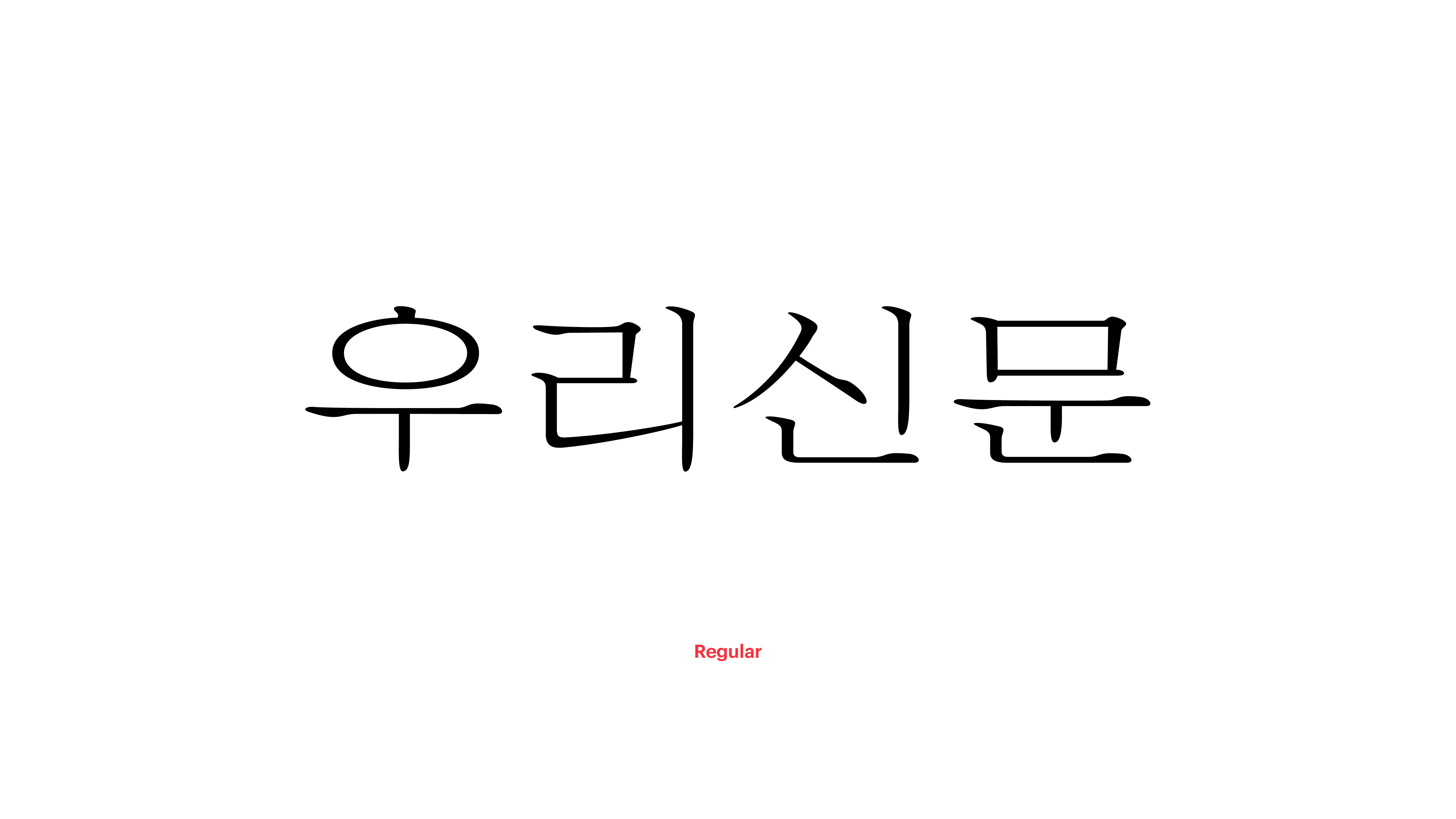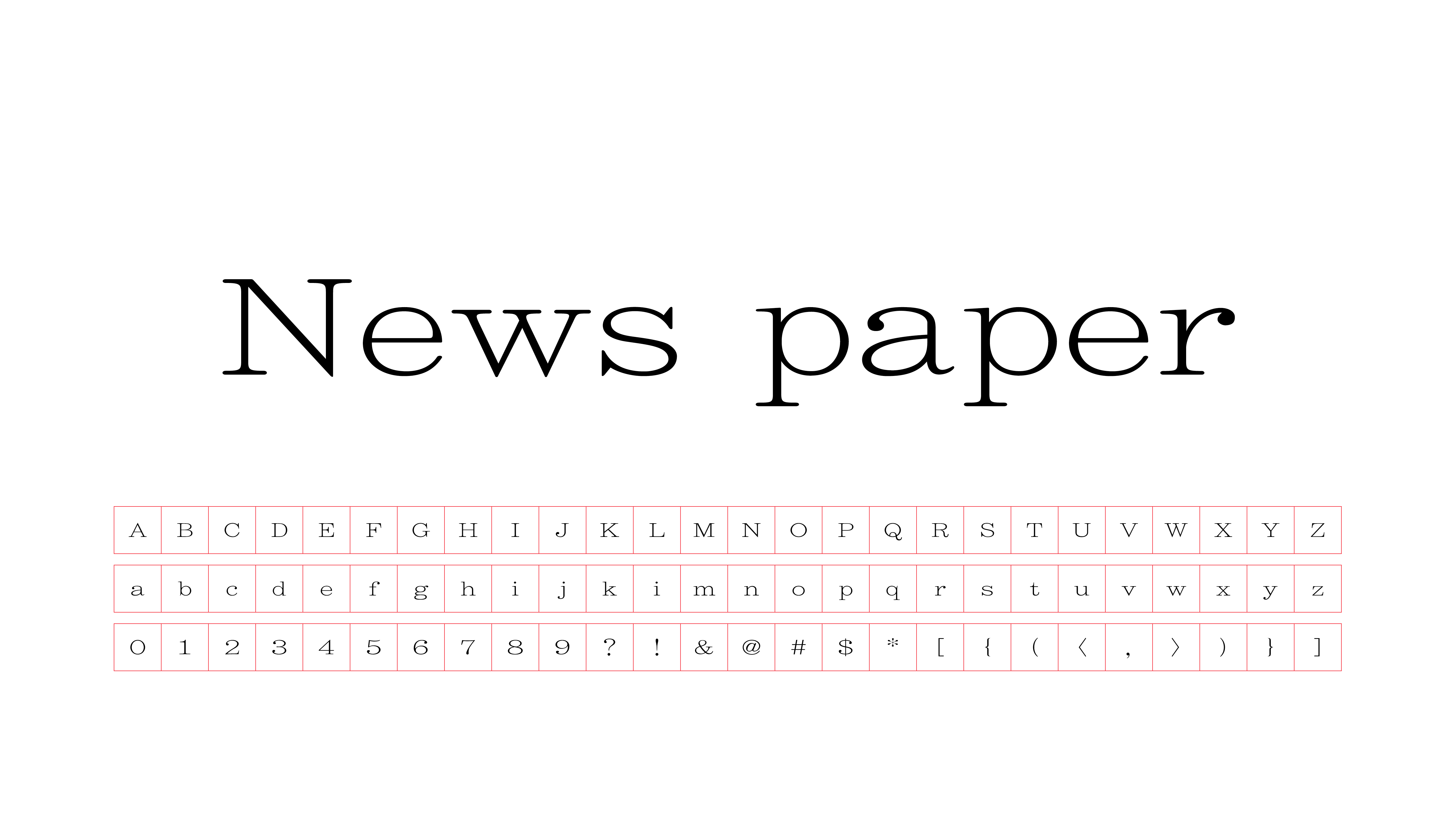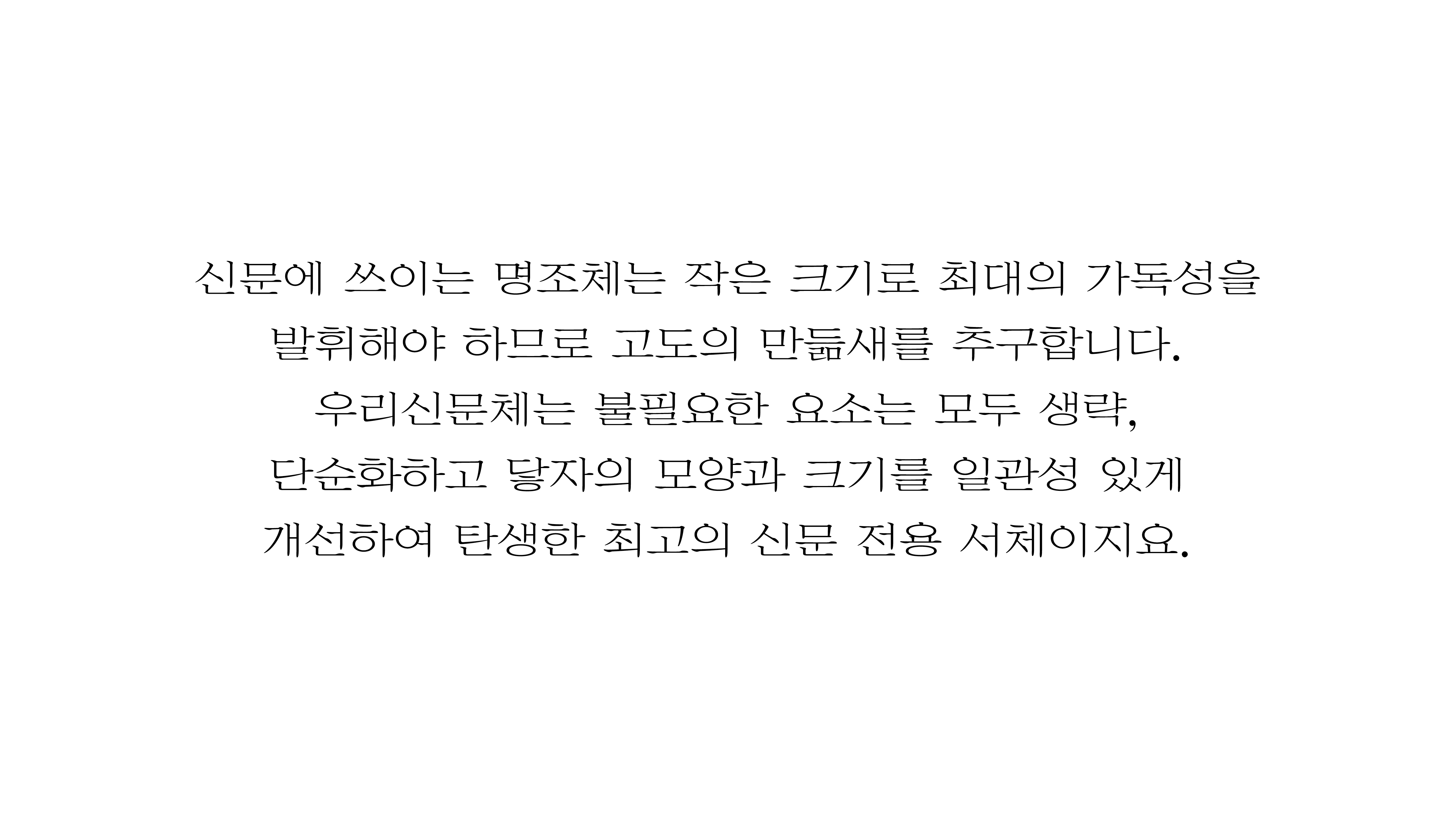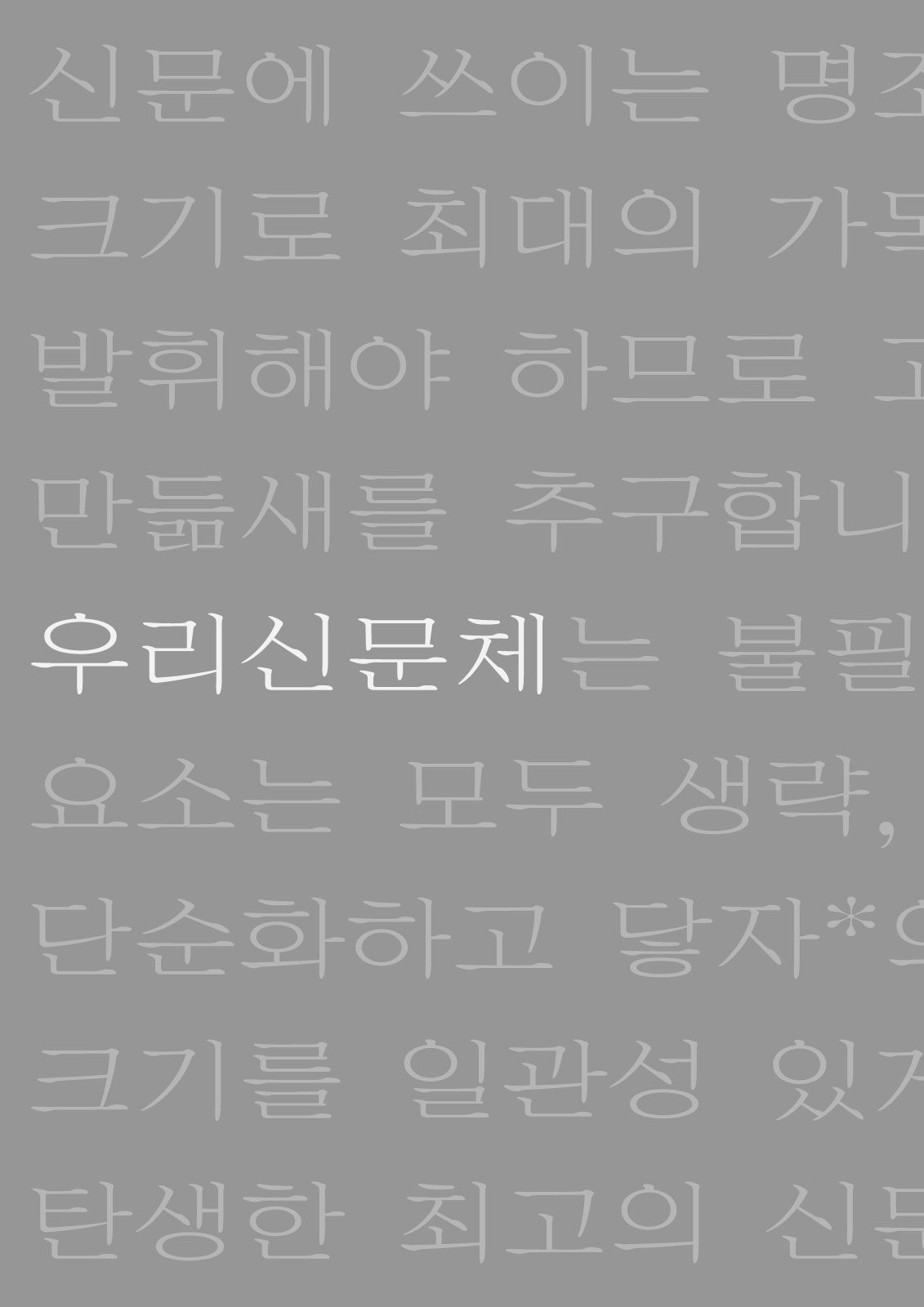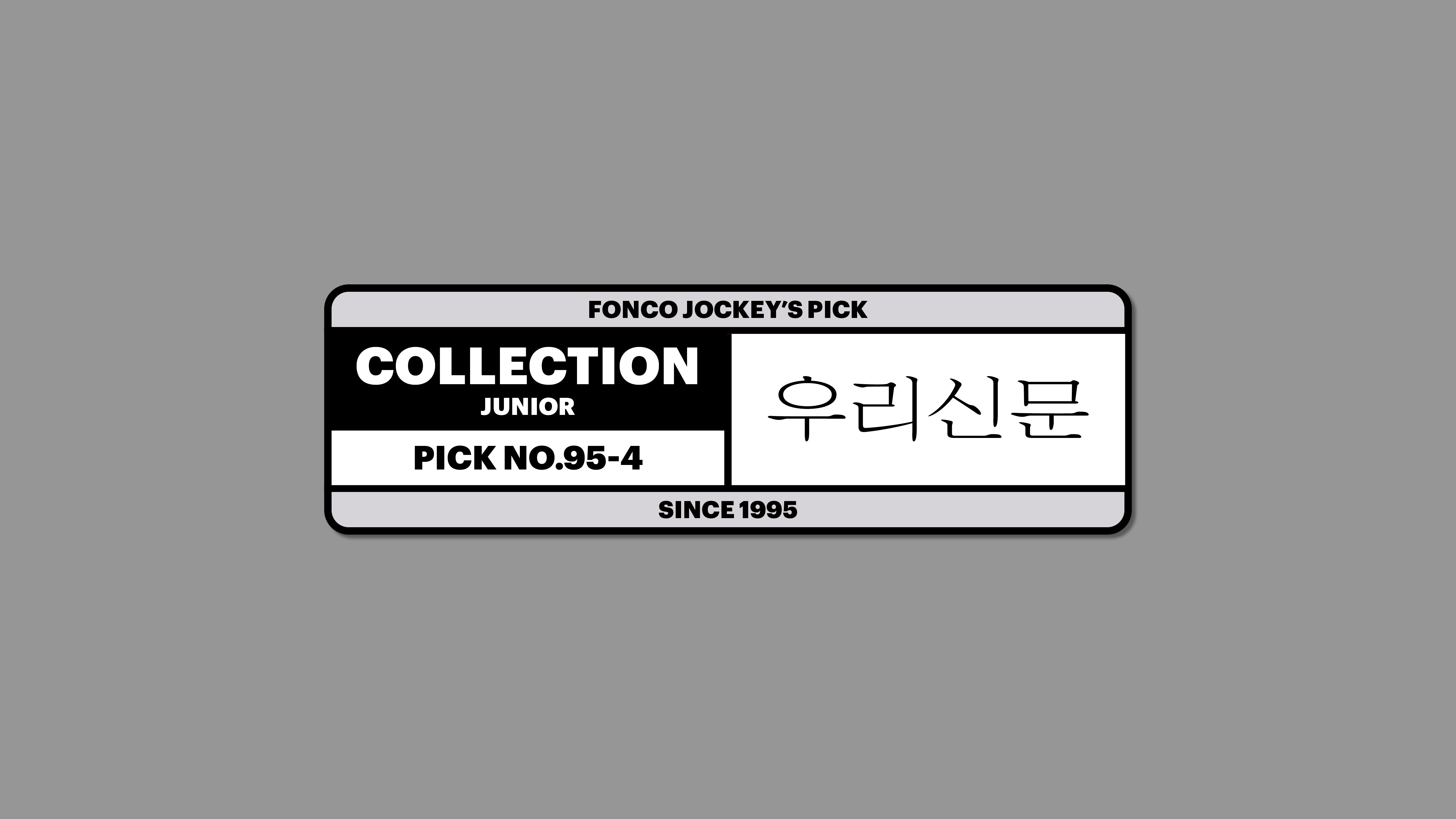
우리신문
1990-1994
Yoon 우리신문
신문에 쓰이는 명조체는 작은 크기로 최대의 가독성을 발휘해야 하므로 고도의 만듦새를 추구합니다. 우리신문체는 불필요한 요소는 모두 생략, 단순화하고 닿자*의 모양과 크기를 일관성 있게 개선하여 탄생한 최고의 신문 전용 서체이지요. *닿자 : 한글 ‘닿소리 글자’의 줄임말, 자음을 시각적으로 일컫는 표현.